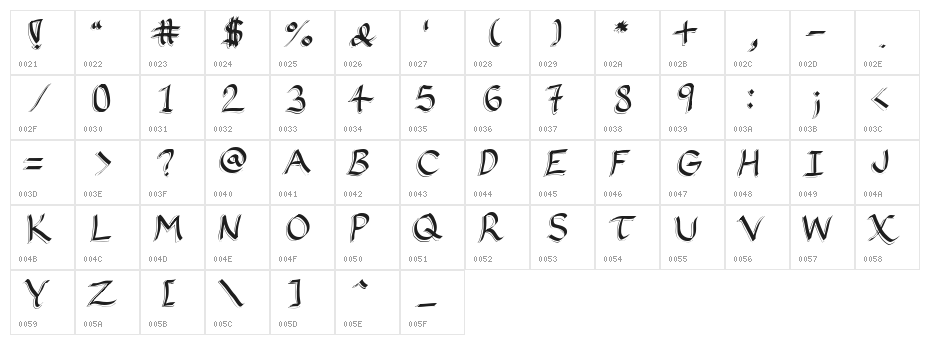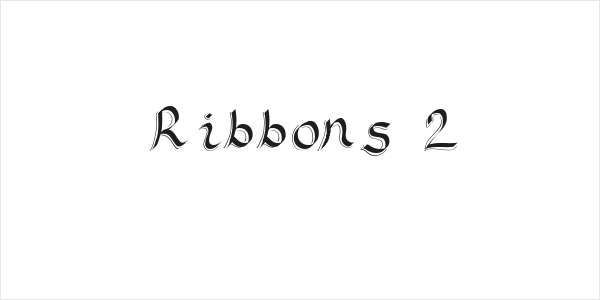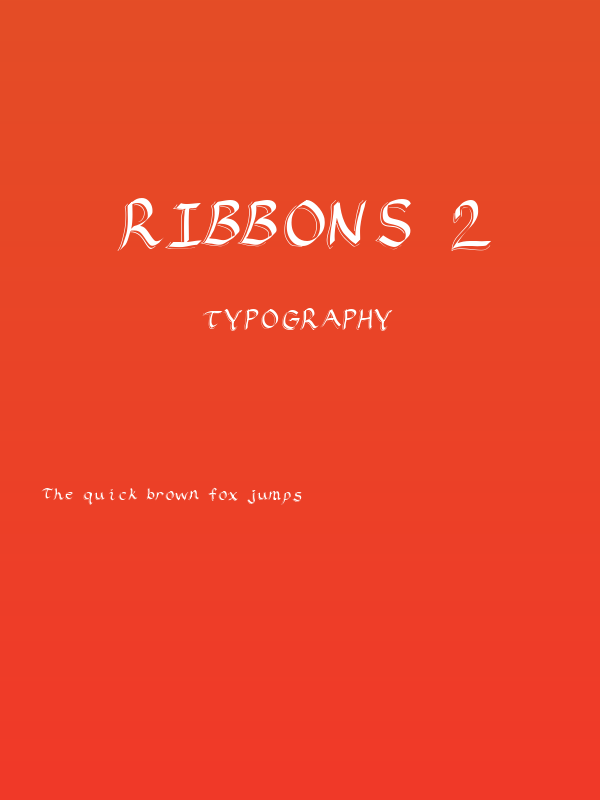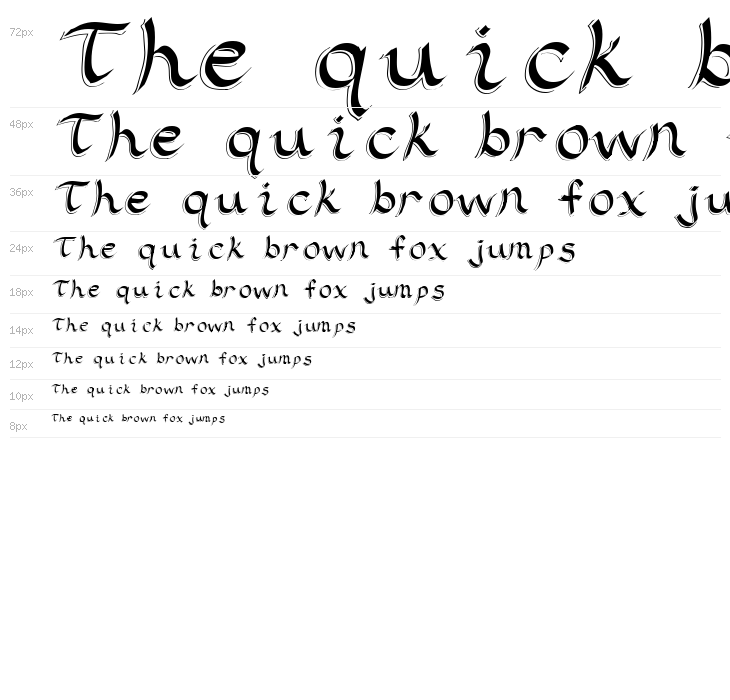
Ribbons 2 Font
| Caso d'uso | Logos, Headlines, Artistic projects |
| Progetti proposti | Ideal for creative projects such as invitations, branding, and artistic posters where a touch of elegance and uniqueness is desired. |